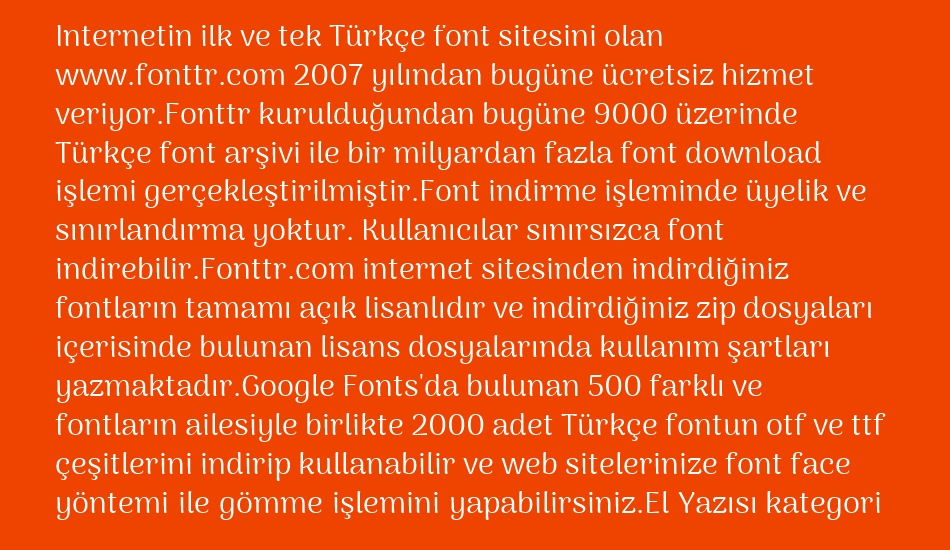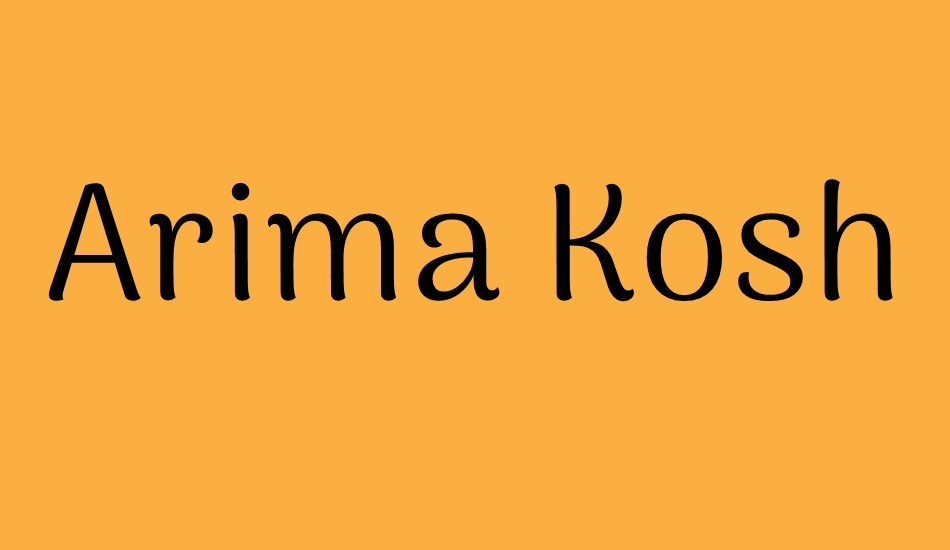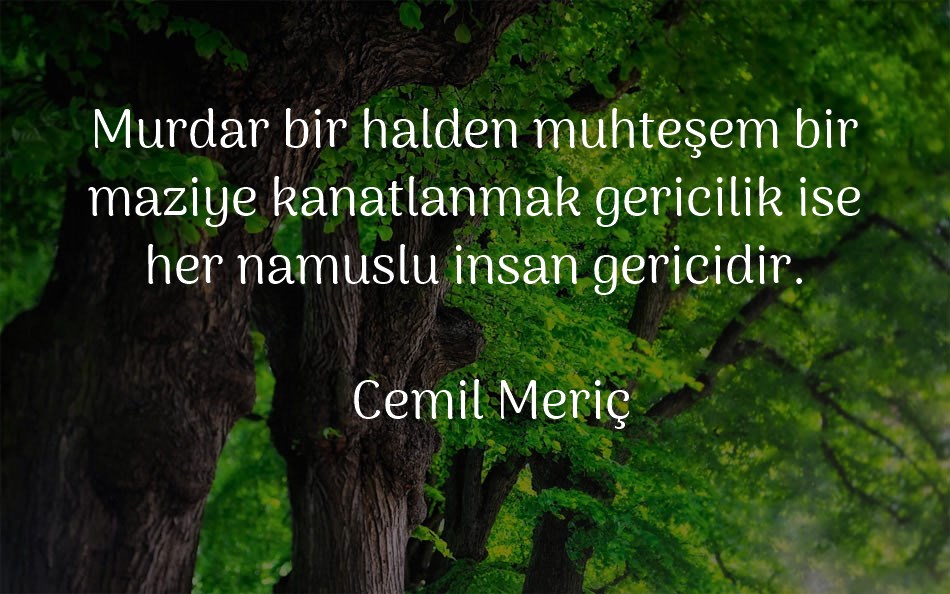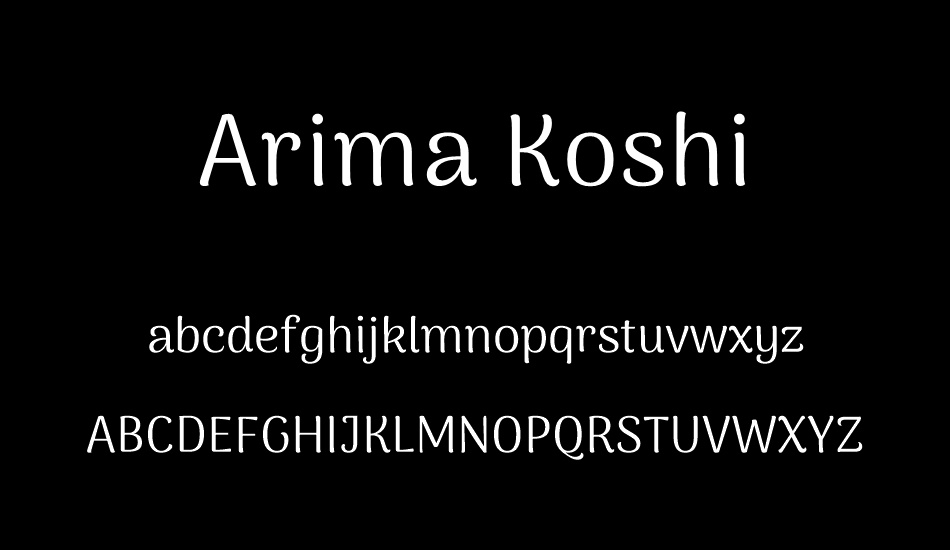
Arima Madurai font
Arima projesinin başlıca ilham kaynağı yumuşak kenarlı ve kaligrafik bir yazı tipidir.
Ekranda iyi bir şekilde oluşturulmasına izin vermek için düşük bir kontrasta sahiptir. Okunabilirlik her zaman merkezi bir endişe kaynağıdır, ancak tasarım, başlık, marka adı ve web'deki benzer kullanımlarda kullanılacak bir ekran yazı tipi olarak tanınabilecek birçok kişiliğe sahiptir. Birincil hedef, sıradan ve profesyonel tasarımcılar ile çınlayan ve tasarım kalitesini düşürmeden popüler olacağını ispatlayacak bir tasarım yaratmaktı. Ailenin her yazı tipi, düşük çözünürlüklü telefonlarda kapsamlı bir şekilde test edildi ve mobil çağda bir web yazı tipi olarak iyi çalışması için rafine edildi. Tasarım testinin ilk turundan itibaren, her yazı tipi ttfautohint ile ima edildi ve Windows kullanıcıları için rafine edildi.
Arima Madurai, Tamil ve Latince senaryolar için geniş bir dil desteğine sahiptir.
Arima Koshi font